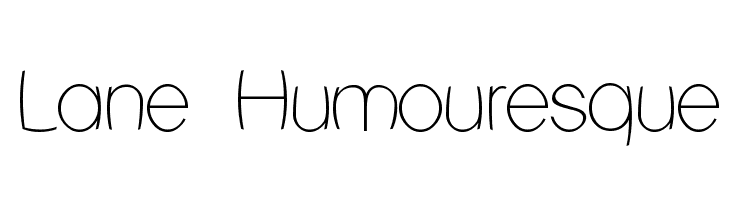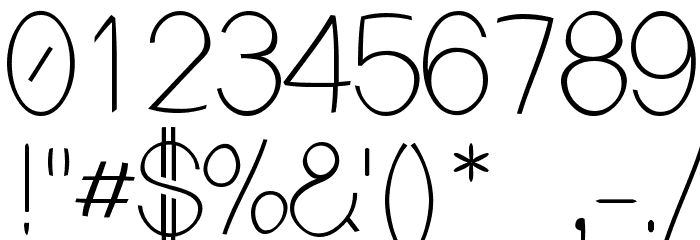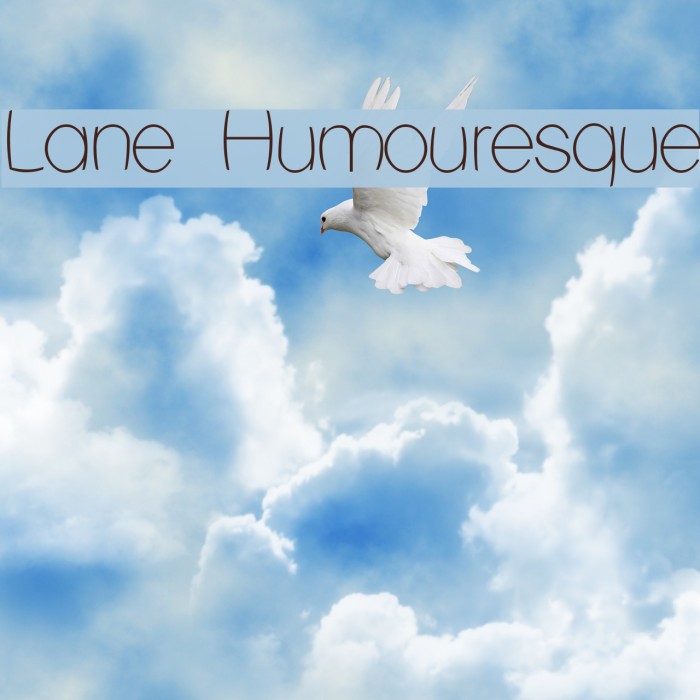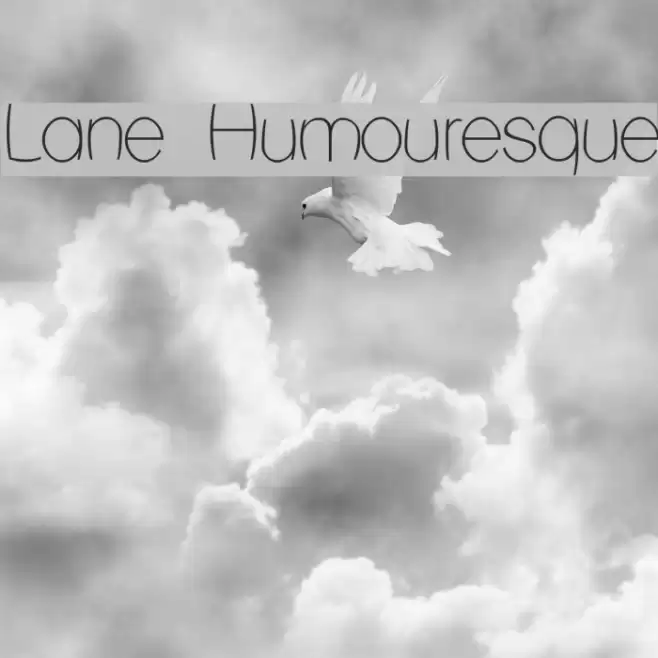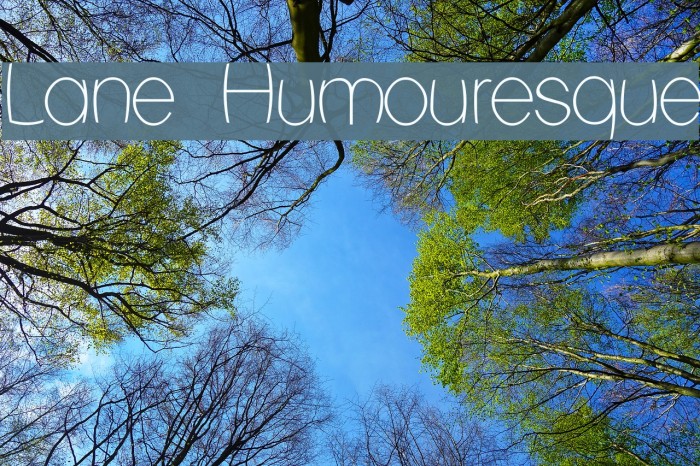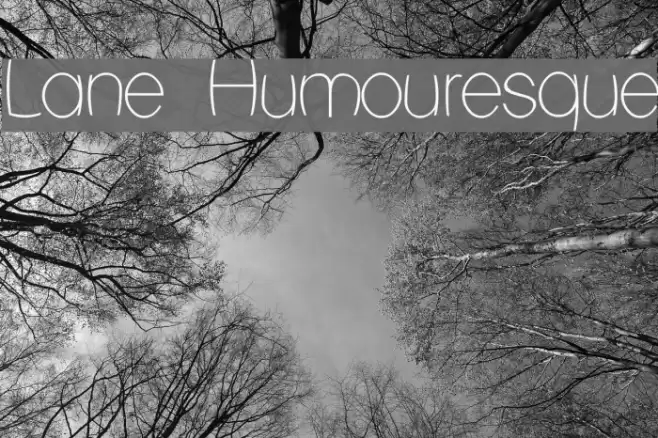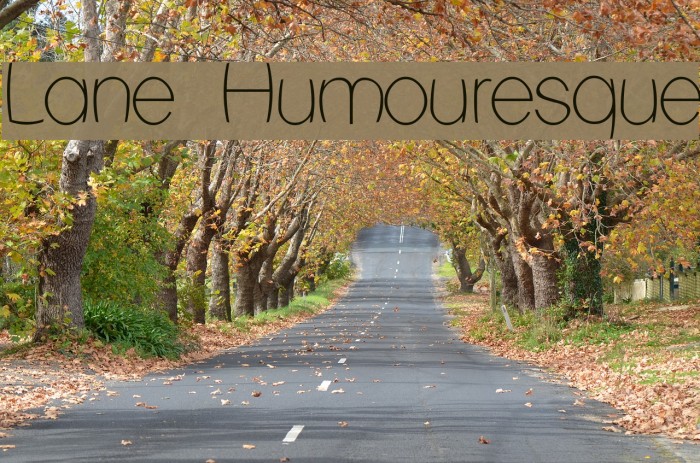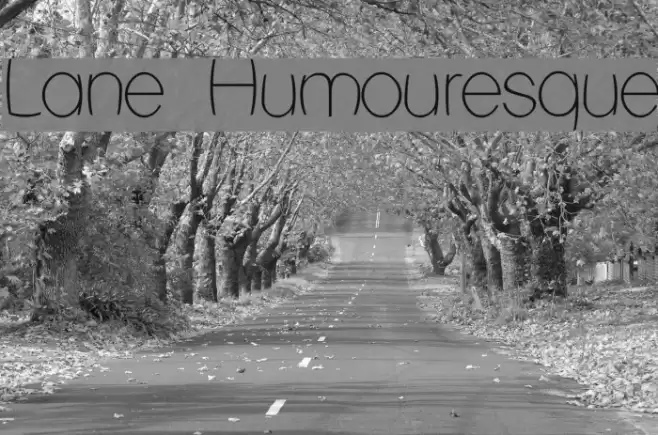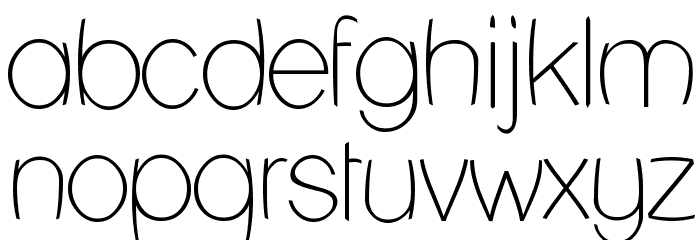
Lane Humouresque Font
| Estilo general | Playful, Modern |
| Caso de uso | Headlines, Logos, Creative Projects |
| Proyectos propuestos | Ideal for children's books, playful branding, greeting cards, and creative posters. |